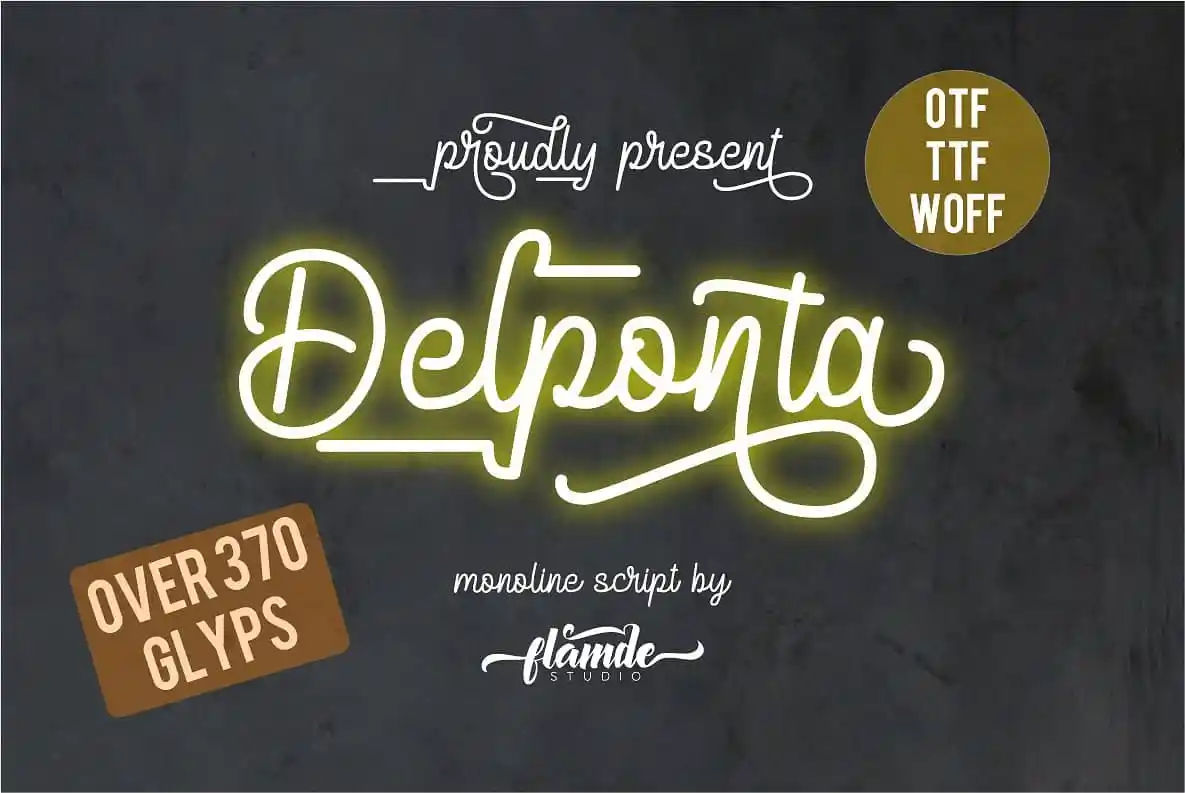
Descubra uma nova opção para seus projetos digitais com a Delponta Script Font. Esta moderna tipografia de escrituração é perfeita para quem busca um estilo único e elegante. Se você está procurando por uma tipografia que se adapte à sua criação, a Delponta Monoline Script Font foi feita para você. Delponta Monoline Script Font, desenvolvida pelo Flamde Studio, é projetada com amor e consistência, resultando em um design simples e fácil de ler. Com as perfeitas curvas que fazem desta fonte uma escolha popular tanto para estilos vintage quanto para trabalhos de casamento ou cartões personalizados. Além disso, a Delponta Monoline Script Font também é ótima para aplicativos como logotipos, posters relacionados à alimentação e bebidas, mensagens pessoais, notas de água, citações, e qualquer outro projeto em que você esteja trabalhando.